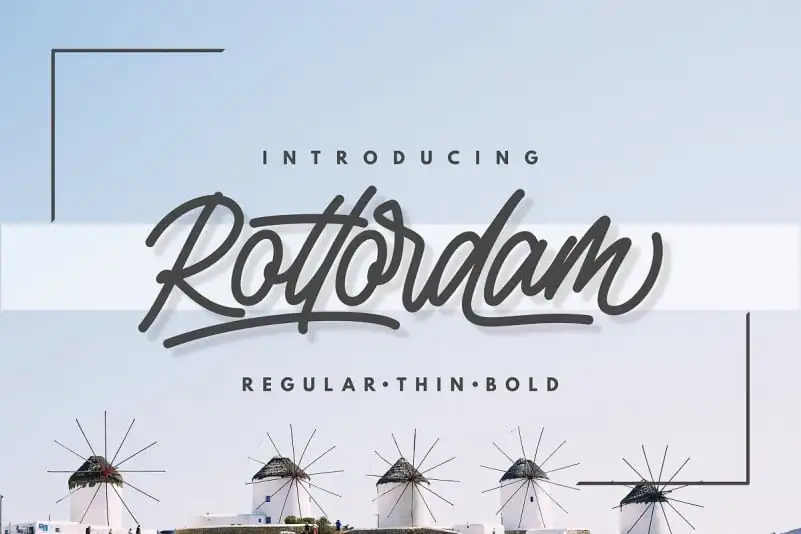
Aqui está uma versão do texto solicitada para a página de download da font ‘Rottordam Script Font’: Introduzimos a você o Rottordam, uma fonte de design de script inspirada no estilo clássico de cartazes. Trabalhados à mão, este tipo de escrita é um verdadeiro prazer olhar e sentir. Além dos caracteres básicos, inclui alternativas do OpenType para cada letra, ligaturas comuns e até mesmo swashes adicionais, tudo isso oferecido em versões maiúsculas e minúsculas, numerais e pontuações. Este tipo de fonte é perfeito para uso em logotipos, cartões de visita, propaganda e design de roupas. Suas variações sofisticadas permitem que você personalize seus projetos de maneira única e expressiva, deixando-o ainda mais à vontade para criar a arte visual que deseja. O Rottordam é um ótimo complemento para qualquer designer gráfico, oferecendo uma mistura interessante entre o clássico e o moderno. Seja você um artista digital ou alguém especializado em design de moda, certamente vai encontrar no Rottordam algo que se adequa perfeitamente a suas necessidades criativas. Se você está à procura de uma fonte de escrita elegante para dar um toque único a seus projetos, então o Rottordam definitivamente merece um lugar em sua estante de recursos digitais.